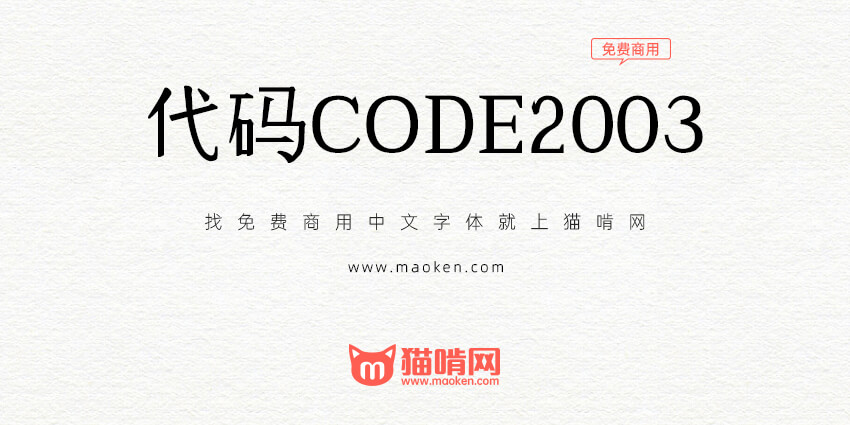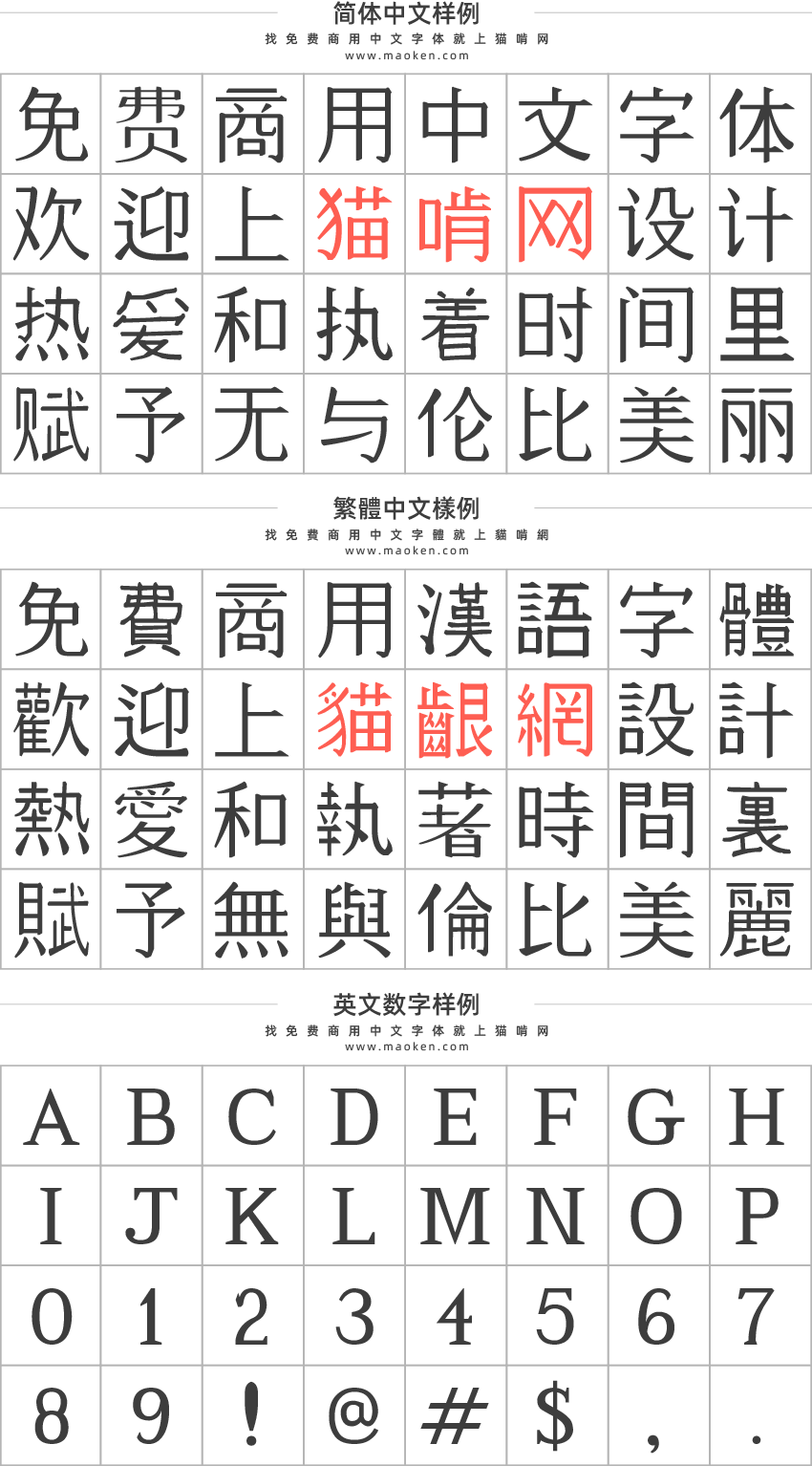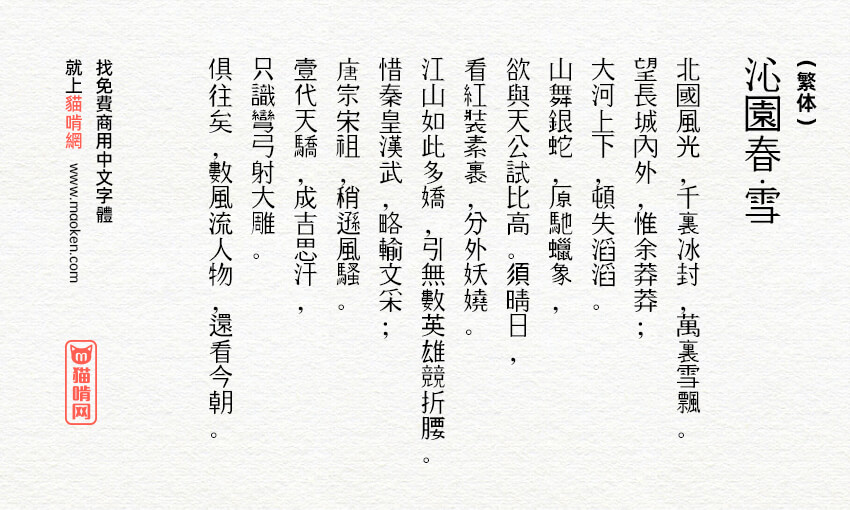
CODE2003:年代久远的经典代码字体免费商用
Code2003这是一种经典的字体,是一种基于unicode的truetype字体,力求最终以一致的字体表示分配给unicode基本多语言平面的所有扩展字符和符号。它的开发人员试图创造一个独特的风格或风味的字符,同时保持忠实于各种脚本的经典字母形式。
丑得可爱
这种看着像拼凑的字体另有一番风味